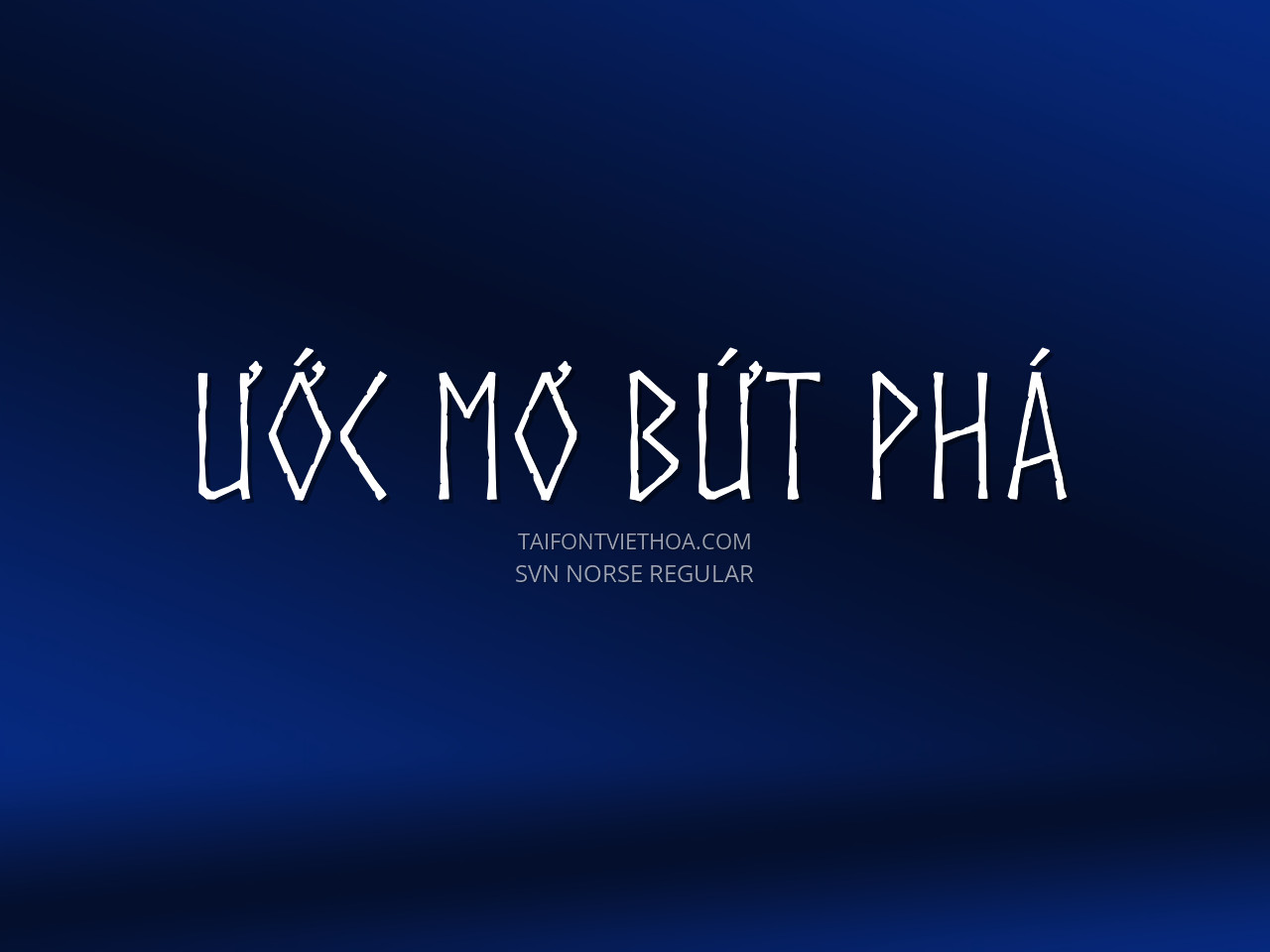
Font việt hóa SVN Norse đầy đủ
Giới thiệu về font SVN Norse Trọn Bộ – Bộ font đa dạng phong cách với tinh thần Bắc Âu
SVN Norse Trọn Bộ là phiên bản Việt hóa của bộ font Norse – một tập hợp các kiểu chữ đa dạng lấy cảm hứng từ văn hóa Bắc Âu với phong cách mạnh mẽ, đơn giản nhưng vẫn đầy cá tính. Bộ font này bao gồm nhiều biến thể từ sans-serif hiện đại đến serif cổ điển, đáp ứng nhiều nhu cầu thiết kế khác nhau, từ thương hiệu đến ấn phẩm truyền thông.
Phiên bản Việt hóa của SVN Norse Trọn Bộ đã được Taifontviethoa.comtuyển chọn kỹ lưỡng, hỗ trợ đầy đủ dấu tiếng Việt và nhiều ngôn ngữ khác, mang đến giải pháp toàn diện cho nhà thiết kế tại Việt Nam trong việc xây dựng dự án đa dạng với tinh thần Bắc Âu đặc trưng.
Đa dạng phong cách – Ứng dụng linh hoạt cho mọi loại dự án thiết kế
Bộ font SVN Norse bao gồm các kiểu chữ từ sans-serif, serif đến display, với các đường nét rõ ràng, tinh giản và cá tính, phù hợp với nhiều lĩnh vực thiết kế khác nhau. Các biến thể font có thể sử dụng cho tiêu đề, đoạn văn bản, logo và các ấn phẩm quảng cáo, mang đến sự linh hoạt và nhất quán trong bộ nhận diện thương hiệu.
Ứng dụng lý tưởng: thiết kế nhận diện thương hiệu, logo, poster, tạp chí, brochure, website và các sản phẩm đa phương tiện. Ngành nghề phù hợp: công nghệ, thời trang, kiến trúc, truyền thông, quảng cáo, và các thương hiệu hiện đại, trẻ trung.